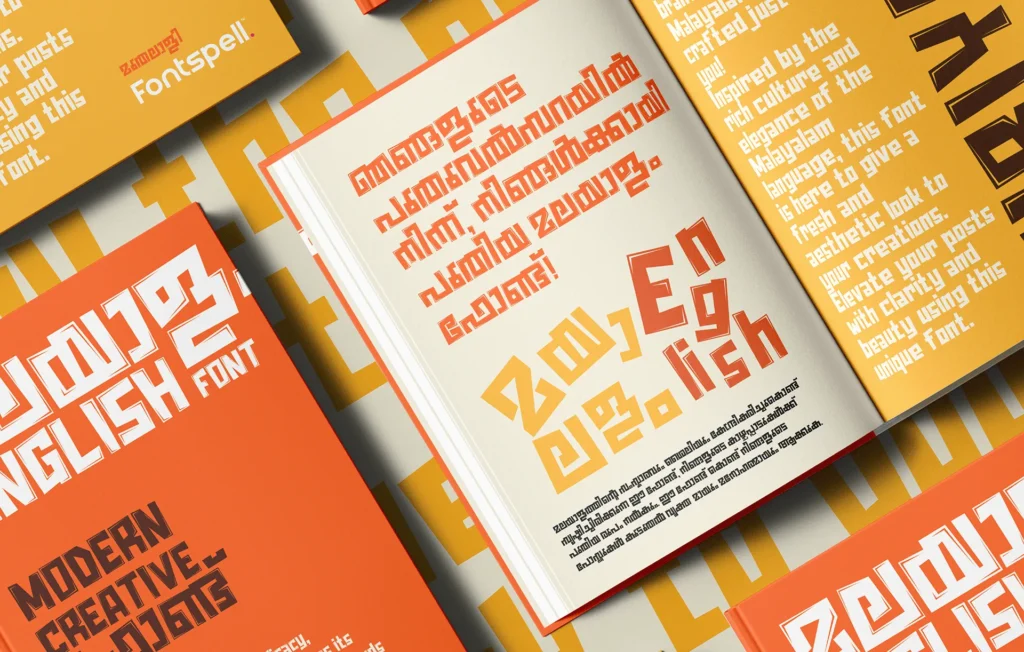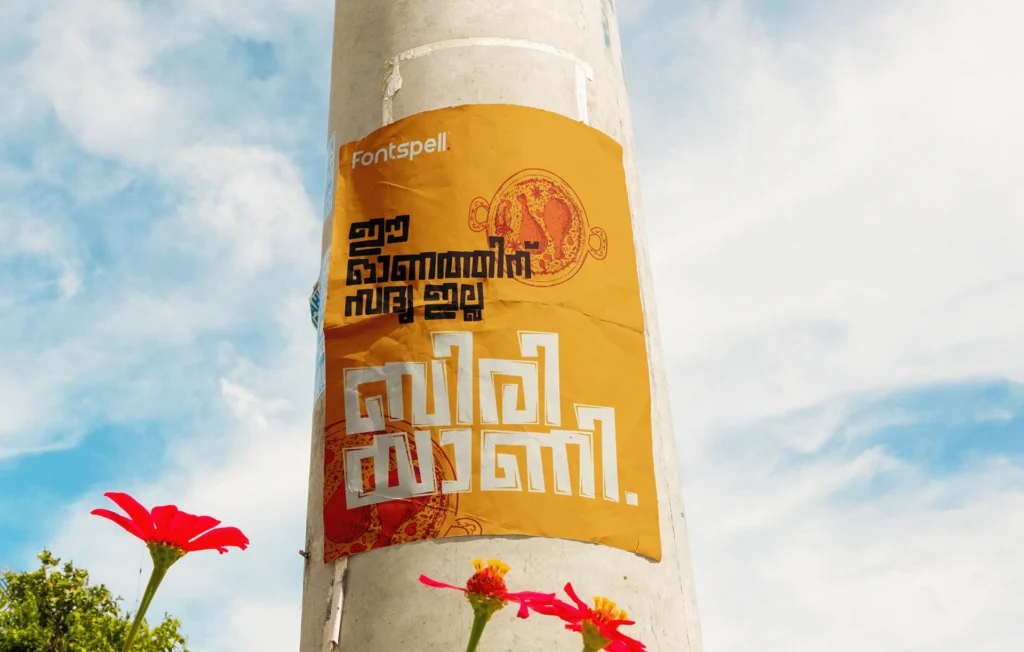
മലയാളത്തിലെ പുതിയൊരു വ്യത്യസ്തമായ മോഡേൺ ഫോണ്ടാണ് ബിരിയാണി. നമുക്ക് ഈ ഫോണ്ടിനെ കുറിച്ച് നോക്കാം, കൂടാതെ ഈ ഫോണ്ട് വച്ചുള്ള തമ്പനയിലിൽ കണ്ടത് പോലെ ഉള്ള പോസ്റ്റർ ഫോട്ടോഷോപ്പിൽ എങ്ങനെ ചെയ്യാമെന്നും, നിങ്ങളുടെ ഫോണിൽ എങ്ങനെ ഇത് ഉപയോഗിച്ച് ഒരു ചെറിയ പോസ്റ്റർ ഉണ്ടാക്കാം എന്നും നോക്കാം
ബിരിയാണി ഫോണ്ടിന്റെ സവിശേഷത എന്നത് ഇത് ഒരു യൂണികോഡ് ഫോണ്ട് ആണ്. ഇംഗ്ലീഷിലും മലയാളത്തിലും ഈ ഫോണ്ട് ഉപയോഗിക്കാം. സിമ്പിൾ ആയി പറയുകയാണെങ്കിൽ ഇത് മൊബൈലിലും വളരെ ഈസിയായി ഉപയോഗിക്കാൻ കഴിയും എന്നതാണ്.